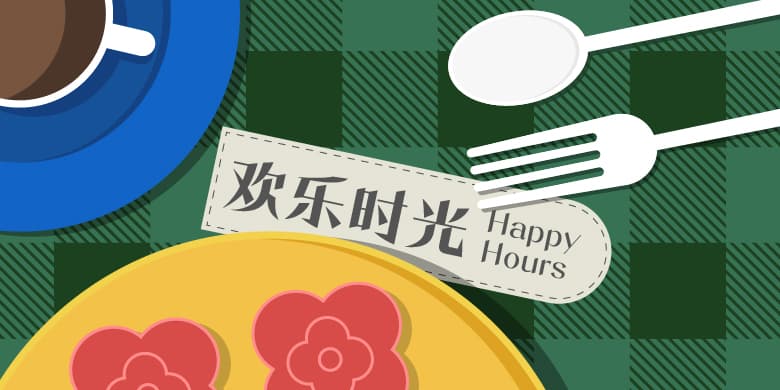
方正潇洒宋家族
品牌:方正字库设计师:郭炳权发行时间:2020字库编码:大陆简体(GB2312-80)、简繁扩展(GBK)分类:创意字体字体属性:精品字
方正潇洒宋家族
潇洒宋设计灵感源于琳琅满目,风度翩翩的男性时装表演,尽显男士的魅力和潇洒气质。潇洒宋将左边部首比例缩小,而夸大强调右边部首的撇、捺的曲线美,形成一款非常潇洒悦目、充满男士风采和时代感的字体。潇洒宋家族含8款字重,适合高级男士用品牌、酒类、时装等商业宣传和包装设计。